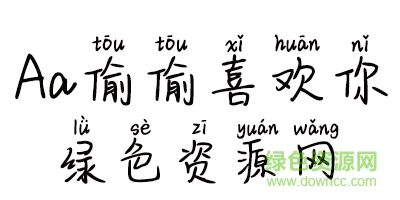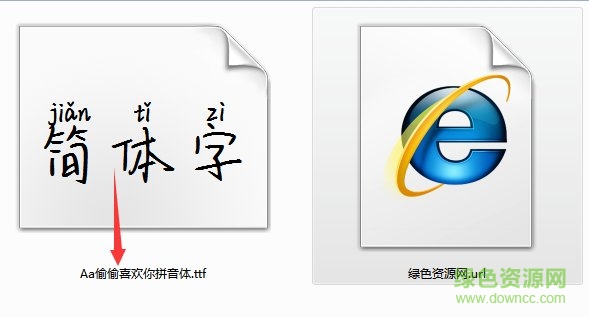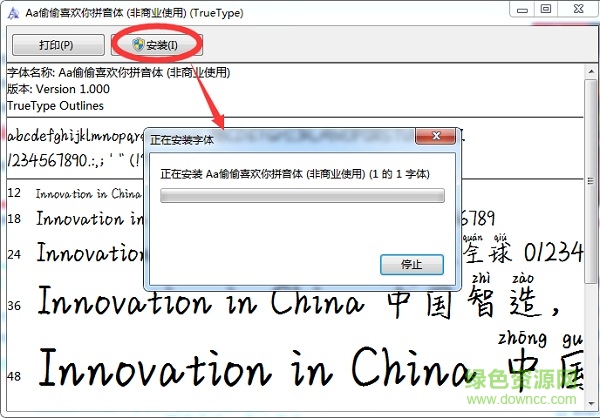
aa偷偷喜歡你拼音體是一個ttf格式的拼音字體資源。使用它輸出的字體包含了拼音和漢子上下兩部分??梢杂米鲈O計,也可以用在教育行業(yè)。歡迎網友們來綠色資源網下載使用。
該字體的線條粗細適中,筆畫結構非常的圓潤,整體看上去非常的流暢,藝術性跟實用性兼有!字體字體是非商業(yè)使用的,建議要商業(yè)使用的小伙伴先獲得授權再使用!
字體家族:Aa偷偷喜歡你拼音體 (非商業(yè)使用)